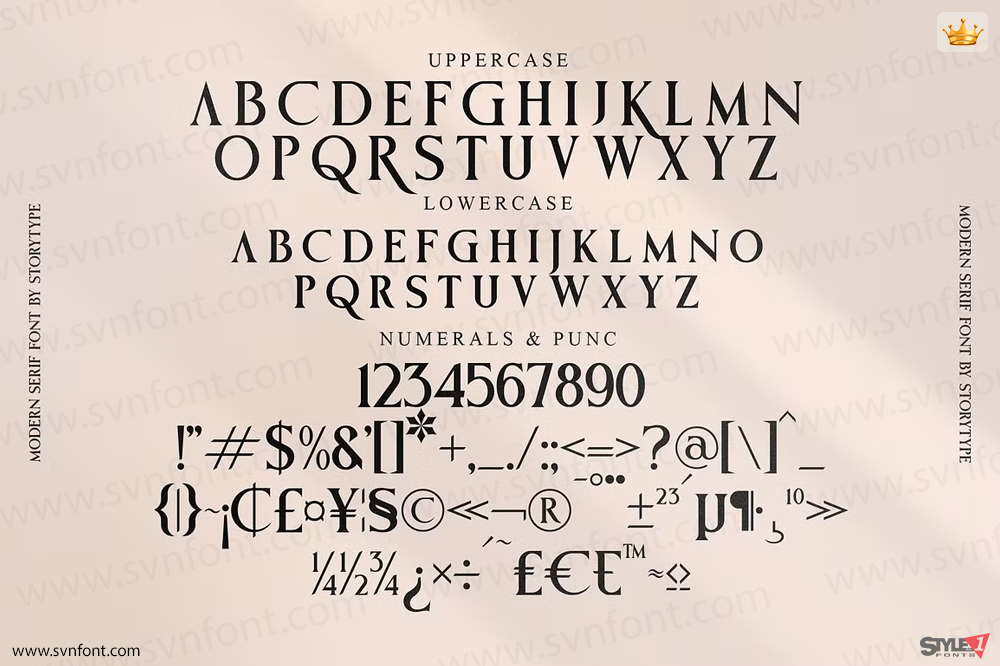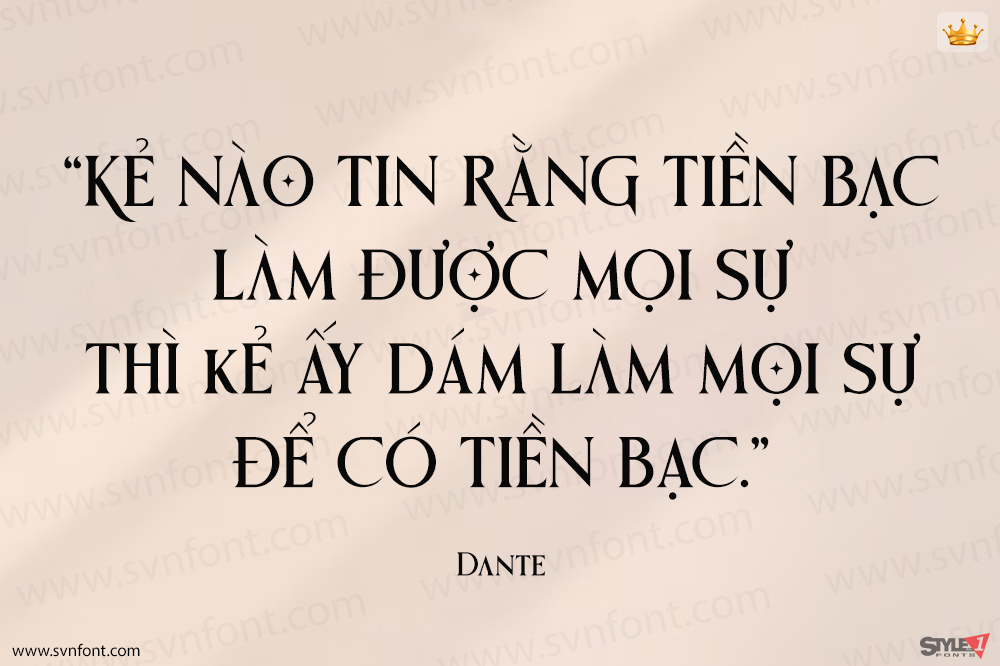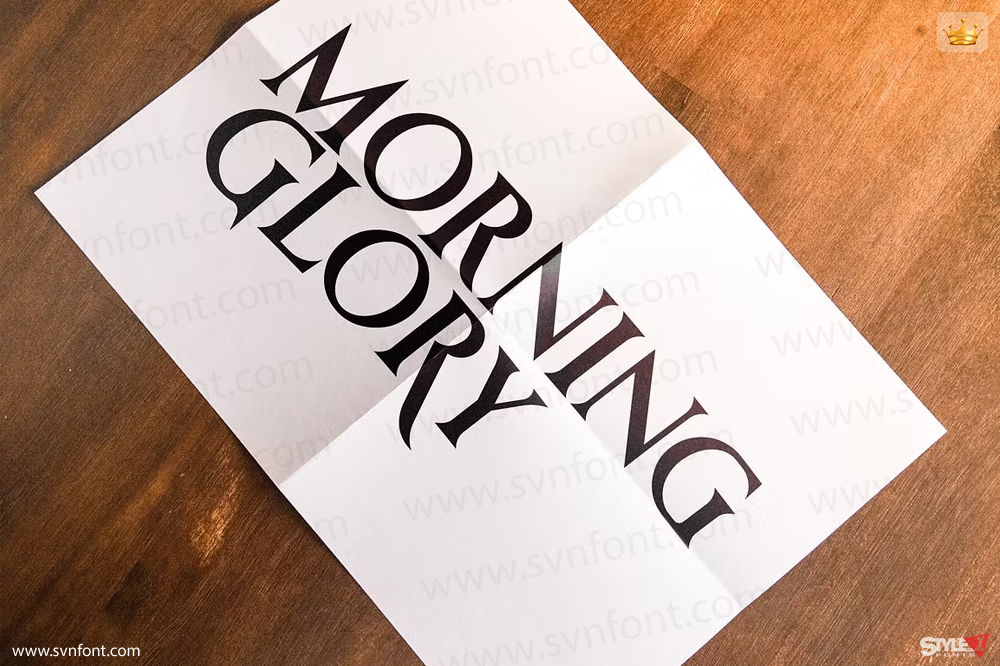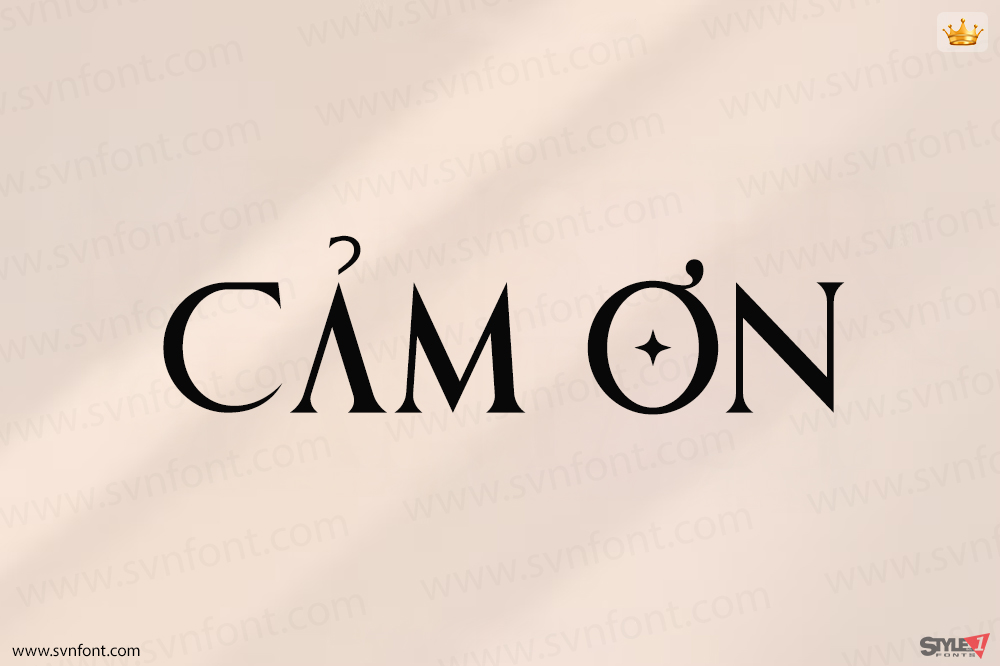
Trân trọng giới thiệu Kiểu chữ MONSTER OF FANTASY, được tạo ra bởi Storytype, một kiểu chữ serif hiện đại và cổ điển mang phong cách độc đáo và vẻ ngoài hiện đại riêng. Kiểu chữ này hoàn hảo cho logo thanh lịch và sang trọng, thiết kế tiêu đề sách hoặc phim, thương hiệu thời trang, tạp chí, quần áo, viết chữ nghệ thuật, trích dẫn và nhiều hơn thế nữa.